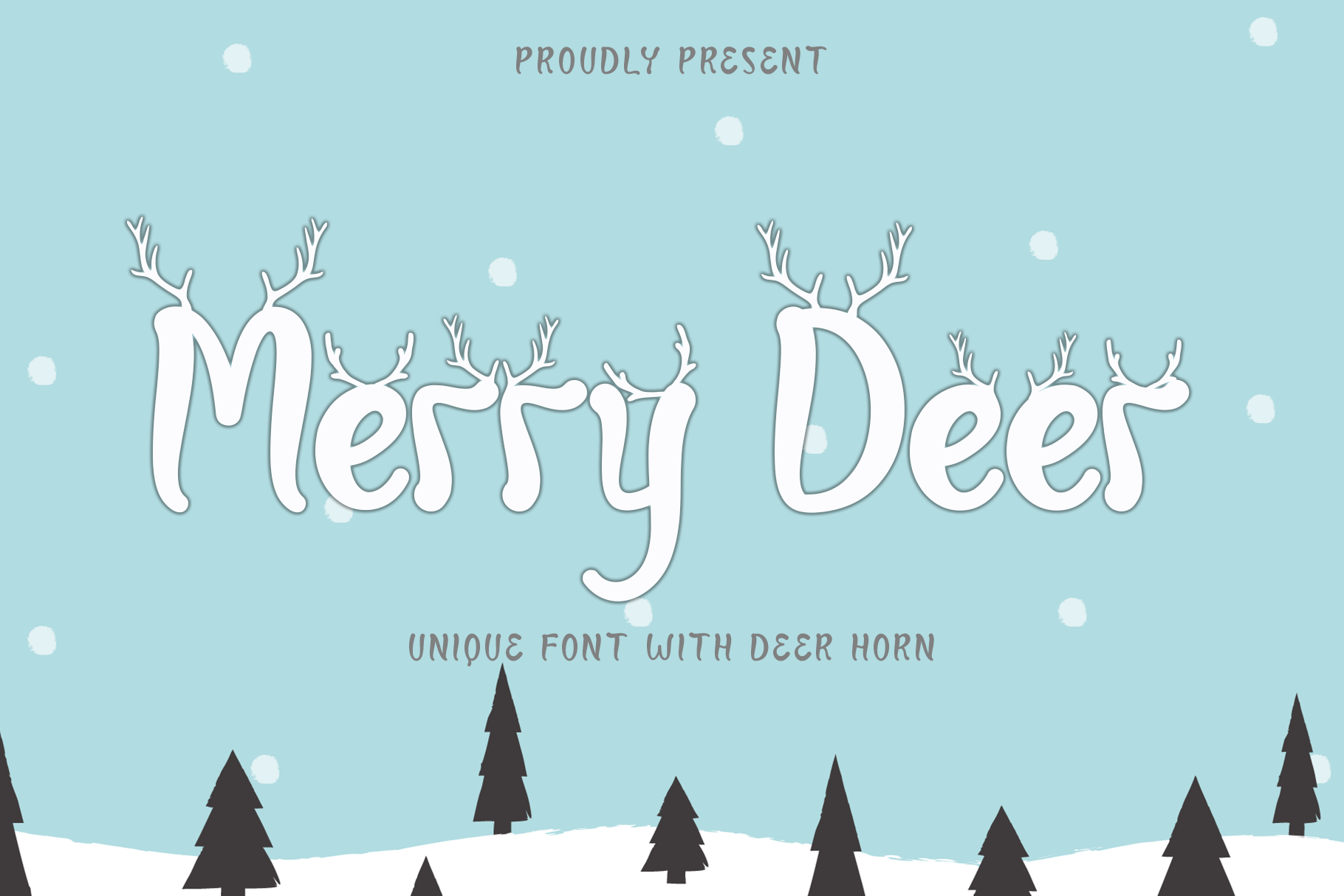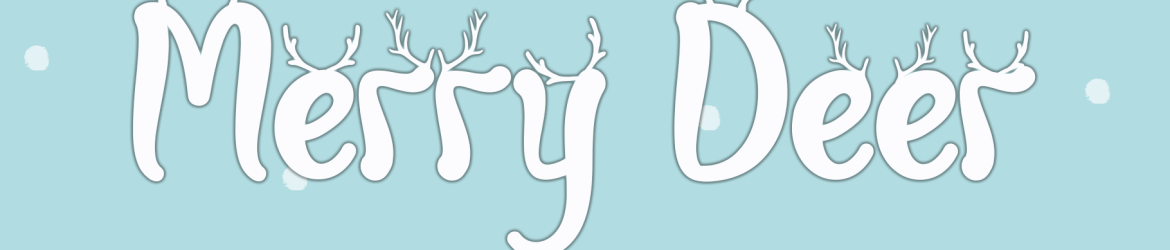
Esta é uma fonte display divertida, elegante e trendy, ideal para decorar textos. A Merry Deer Font é PUA codificada, o que significa que você pode acessar todos os gílios e swashes com facilidade! Ela possui um estilo incrivelmente suave e apropriado para criar designes de alta qualidade. Esta fonte será um ótimo complemento para qualquer projeto visual, seja uma marca empresarial ou uma página web moderna. Estamos certos de que você irá adorar sua simplicidade encantadora e o poder que ela tem para tornar os seus projetos ainda mais atraentes. Que tal incluir esta fonte em seu próximo trabalho?